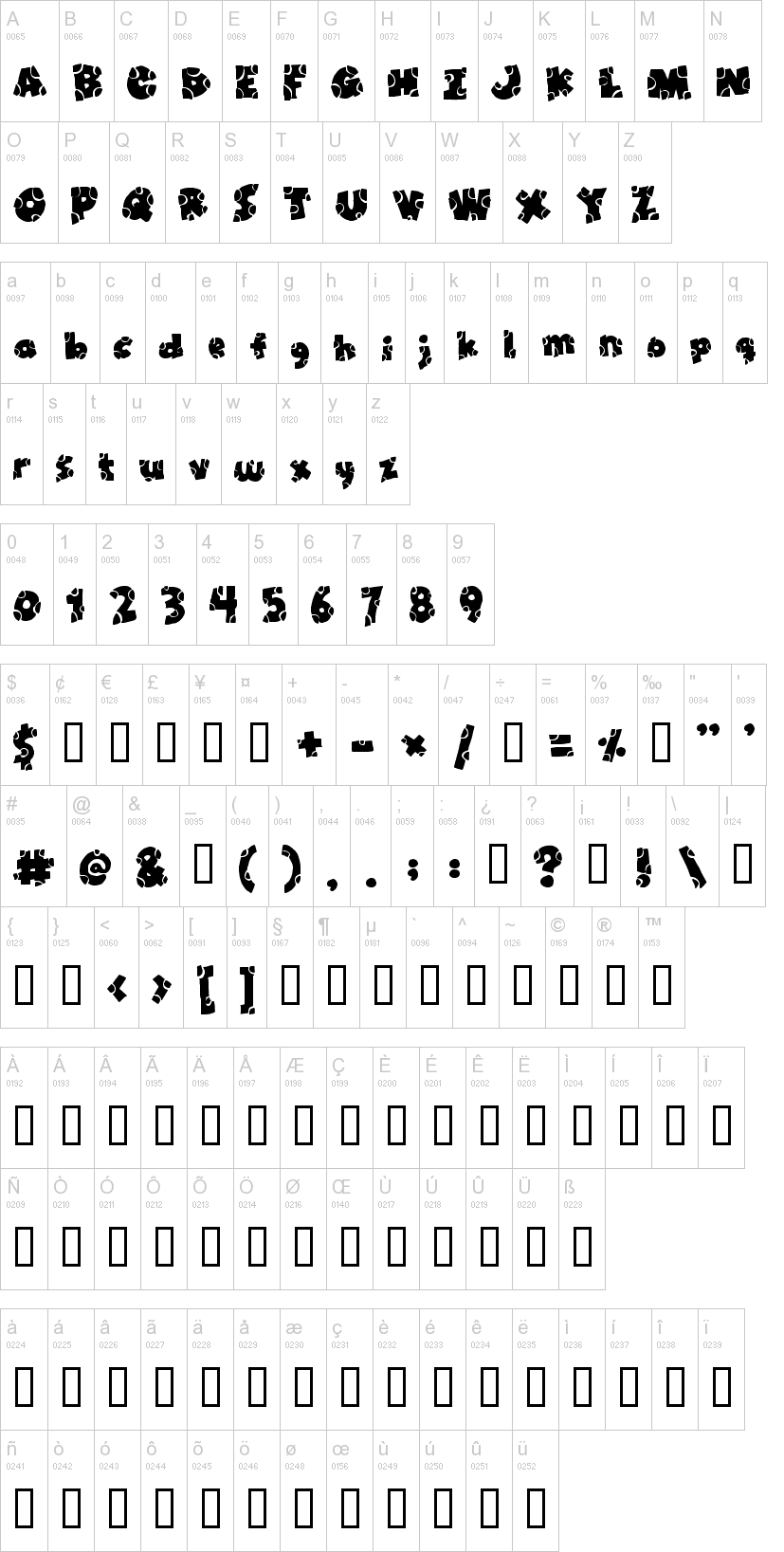
Broken Toys
Broken Toys 是一种免费的手写字体,它的风格非常具有个性和艺术感。与常规字体不同,它有一些不规则和错位的线条,让它看起来像是手写笔触。 这种字体的字母形状和大小不完全相同,因此在使用时会产生一种独特的效果,给人一种非常别致的感觉。它适用于很多不同的设计项目,例如海报、卡片、标志和宣传册等。它的使用可以为设计带来一些个性和艺术感,让设计作品更加醒目和引人注目。
Broken Toys是一款非常不错的手写艺术字体,具有很好的视觉感,适合于文化类的宣传设计、商业类品牌的广告和产品包装设计以及个性化文字排版等较多场景。